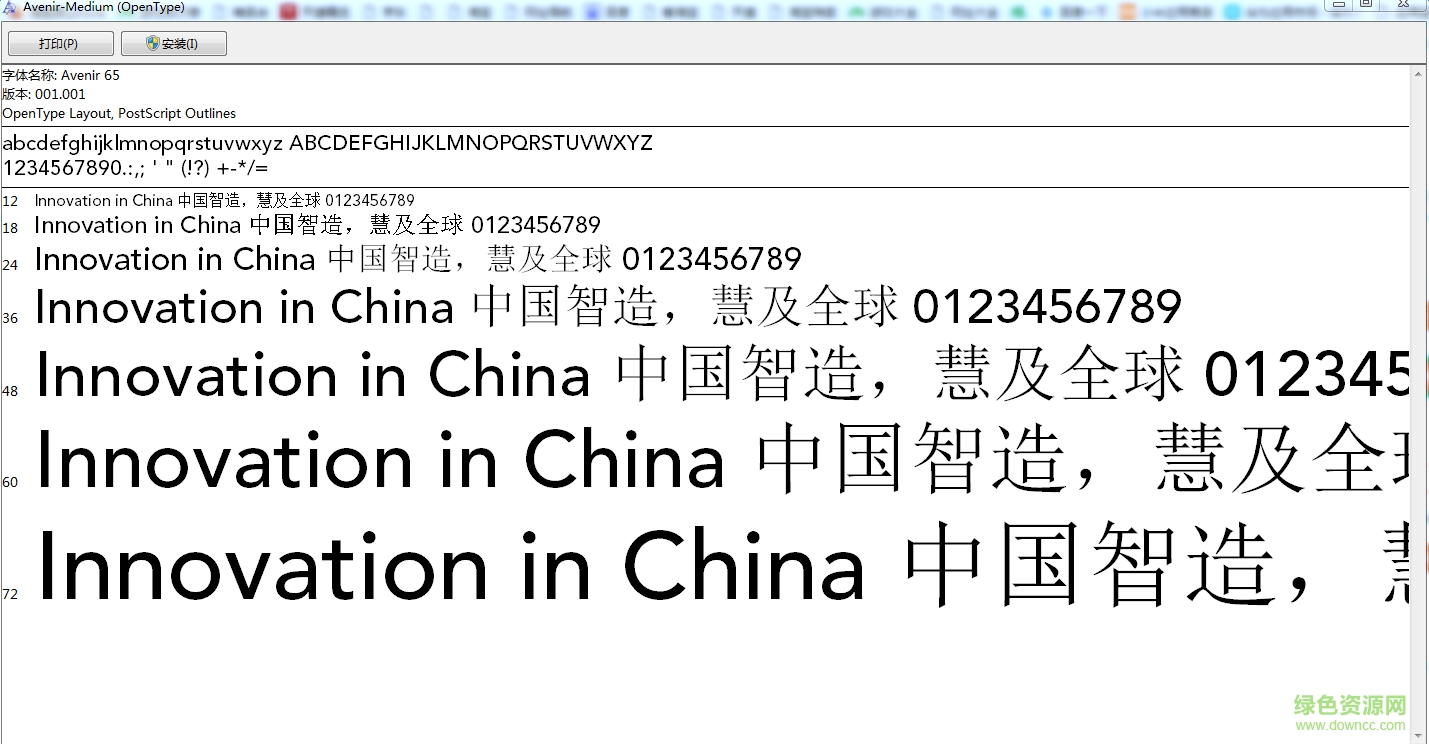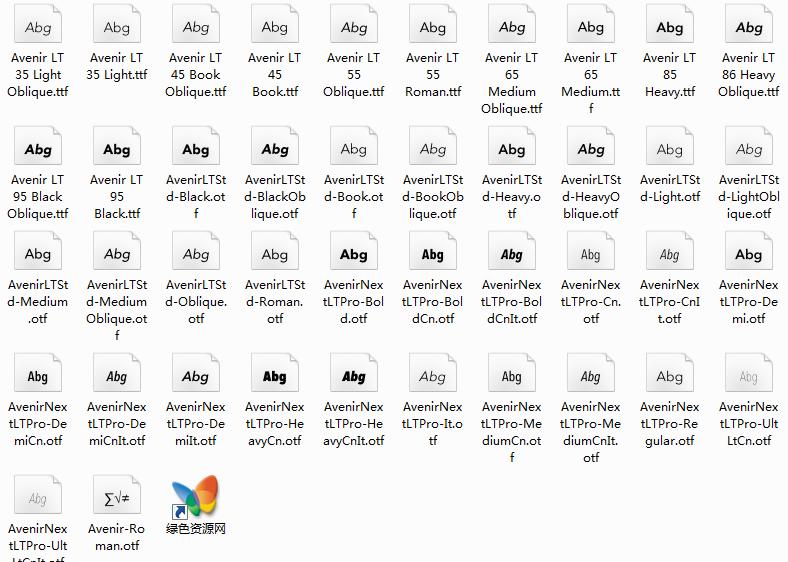
avenir被視為現(xiàn)代主義在字體設(shè)計界的典型代表,是一款經(jīng)典的無襯線字體,剝除了多余的細節(jié),以標準的幾何形體做結(jié)構(gòu)。反而是這種沒有任何風(fēng)格的字體形式成為了一種風(fēng)格。越簡約,越現(xiàn)代,因此常用于現(xiàn)代企業(yè)的logo設(shè)計、雜志排版、導(dǎo)視系統(tǒng)等!